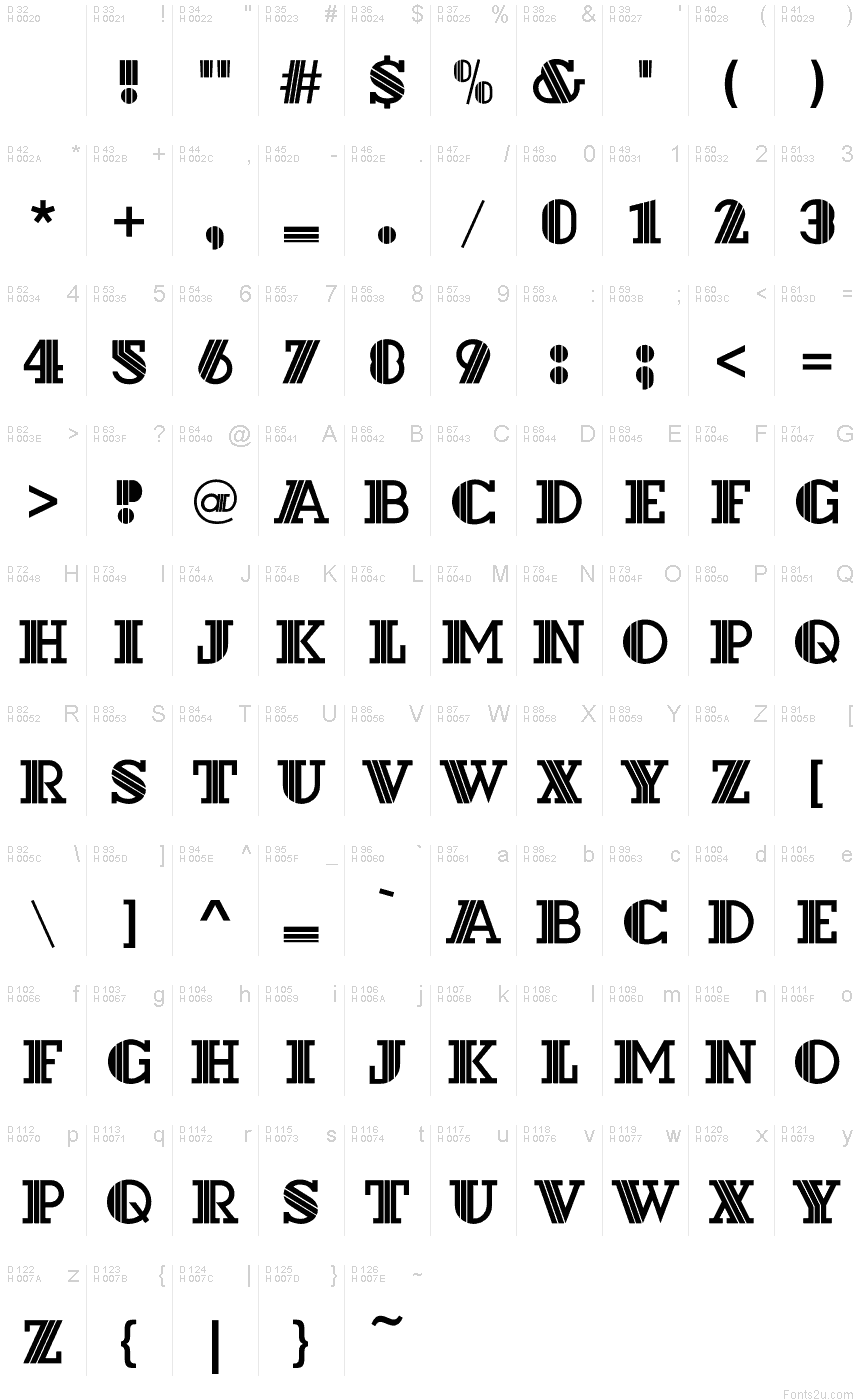
UKIJ Kufi Chiwer von der Uyghur Computer Science Association ist eine kostenlose Kufi-Display-Schrift mit einem strengen, architektonischen Rhythmus. Die Buchstaben sind aus rechtwinkligen Ecken und hohen, aufrechten Strichen aufgebaut, während feine vertikale Streifen im Inneren der Formen der Schrift einen gewebten, ornamentalen Puls verleihen, der tief in der geometrischen islamischen Kalligrafie verwurzelt ist.
Diese Mischung eignet sich hervorragend für Plakate, kulturelles Branding, Buchtitel, Titelkarten und kurze redaktionelle Überschriften, bei denen das Muster einen Teil der visuellen Gestaltung übernimmt. Als kostenloser Font ist er zudem ideal für Logos, Monogramme und knappe Verpackungsdetails geeignet, da die kompakten Blockformen und wiederholten inneren Linien schnell für eine starke grafische Wirkung sorgen.